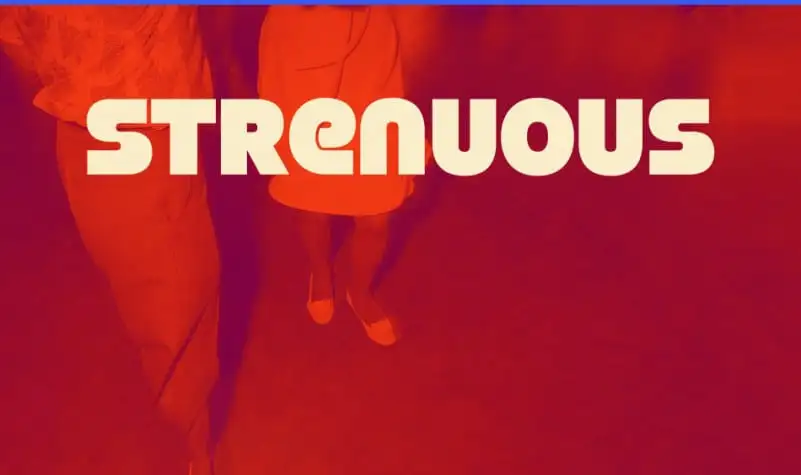
Strenuous Display Font – Fonte Grátis
Strenuous Display Font
A fonte ‘Strenuous Display Font’ é uma sugestão para designers que desejam adicionar um toque peculiar às suas criações digitais. Inspirada na película “Black Eye”, esta fonte de abertura tem um design divertido e criativo, certamente apropriado para headlines ou qualquer outra utilização onde deseje-se chamar a atenção do público. A curiosidade vem da sua origem nos estudos científicos que descobriram uma característica única na fonte. É descrita como sendo “sólida” e “superbad”, não só pela designação de seu nome, mas também pelos comentários dos especialistas em tipos de letras. Estas atribuições são um bom exemplo do quanto ‘Strenuous Display Font’ pode ser versátil e atrativa. Perfeita tanto para uso em aplicações web como em criação de impressões digitais, esta fonte é perfeitamente adaptável à necessidade específica da sua aplicação. Se você está procurando uma alternativa atraente que não seja apenas clássica ou formal, ‘Strenuous Display Font’ pode ser exatamente o que você precisa. Seja para criar um visual chamativo em sua página web ou para adicionar uma personalidade única à sua próxima arte digital, este é um excelente recurso. Não se esqueça de verificar os detalhes inclusos nos arquivos zip para obter mais informações sobre como melhor usá-lo.